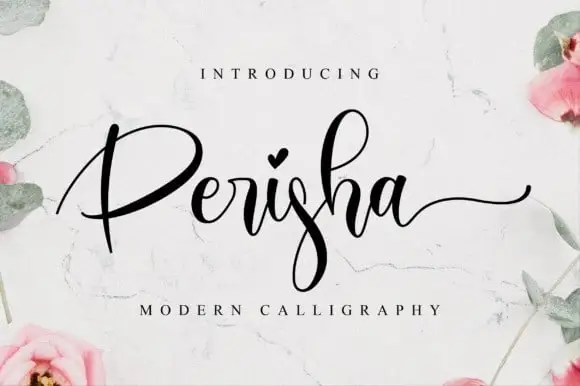
Perisha Calligraphy Font – Download Grátis
A Perisha Calligraphy Font é uma novidade no mundo das fones de script. Feita pela NissaStudio, esta fonte combina elementos do clássico com a modernidade, criando um resultado único e inovador. Seu design tem um traço não perfeito, que daria ao texto uma sensação de dança quando usado nas letras. As linhas são suaves, limpas e simples, o que a torna ideal para diversidades de uso, desde cartões de casamento e convites até menus expandidos, logotipos e mensagens personalizadas. A NissaStudio trouxe uma atmosfera leve e criativa às fones de script, fazendo da Perisha Calligraphy Font um recurso valioso para designers gráficos. Sua simplicidade não significa falta de profundidade; ao contrário, ela permite que o designer se destaque com sua personalização e arte. O perfeito equilíbrio entre a elegância clássica e a modernidade é o ponto forte desta fonte criativa, tornando-a uma escolha natural para qualquer projeto gráfico.